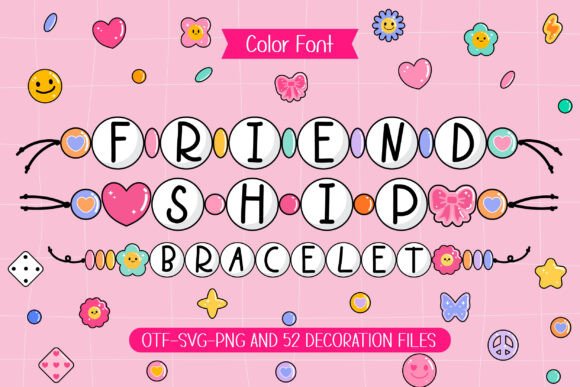
Friendship Bracelet
適切なデザイン要素を見つけるのは難しい場合がありますが、Friendship Braceletは作品を即座に引き立てる優れたコレクションを提供します。
POD(オンデマンド印刷)製品、結婚式の招待状、またはソーシャルメディアのグラフィックを作成している場合でも、Friendship Braceletは理想的です。